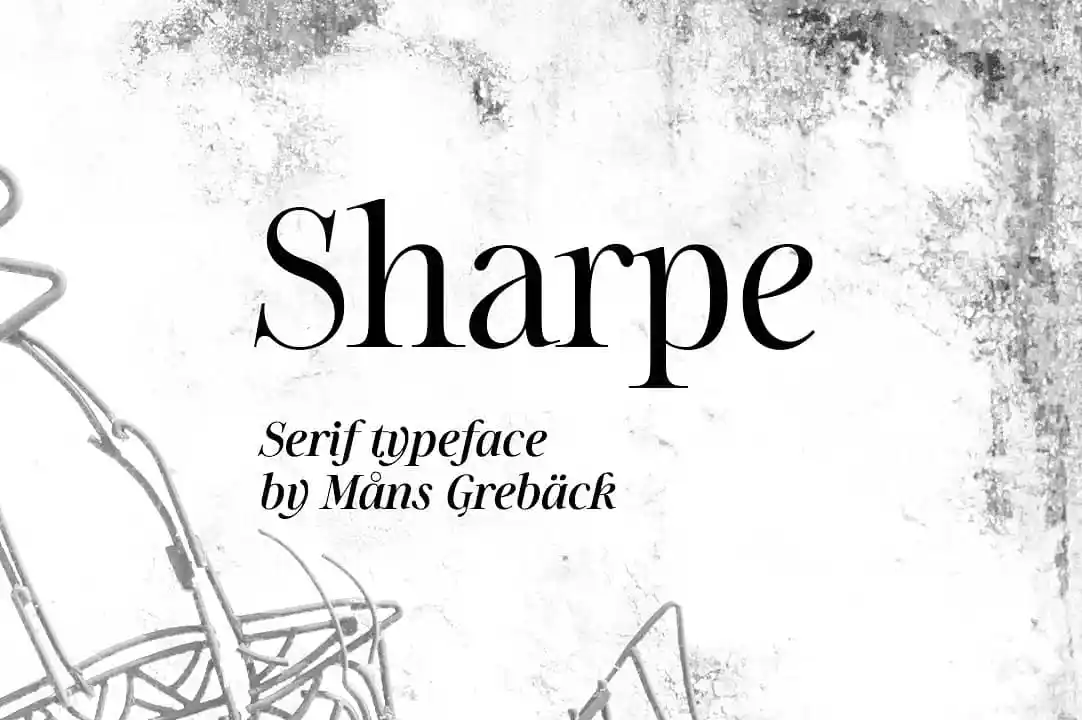
Sharpe Font Family – Fonte Grátis
Sharpe Font Family
Olá, estou aqui! Sharpe é uma família de tipo serifada elegante criada por Mans Greback durante os anos 2018 e 2019. Este tipo deixa claro e agudo, com formas de letras vivas e brilhantes, mas mantendo um fundo conservador. As cinco pesos do tipo se equilibram maravilhosamente uns contra os outros, cada peso possui uma equivalente itálico, totalizando dez estilos, desde o finíssimo até o grosso. Cada estilo contém numerais, símbolos, pontuação, ligaduras e suporte para um amplo range de idiomas. Sharpe é perfeito para se tornar a escolha ideal para seu próximo projeto editorial, gráfico ou tipográfico. Seu contraste harmonioso permite que você personalize sua identidade visual de maneira única, garantindo sempre uma aparência elegante e sofisticada. Com um amplo leque de opções de estilos disponíveis, Sharpe tem o poder de atender a qualquer necessidade gráfica que possa surgir. Sua precisão e simplicidade tornam Sharpe não apenas uma fonte elegante para uso diário, mas também uma escolha inteligente para qualquer projeto que exija profissionalismo e resolução.